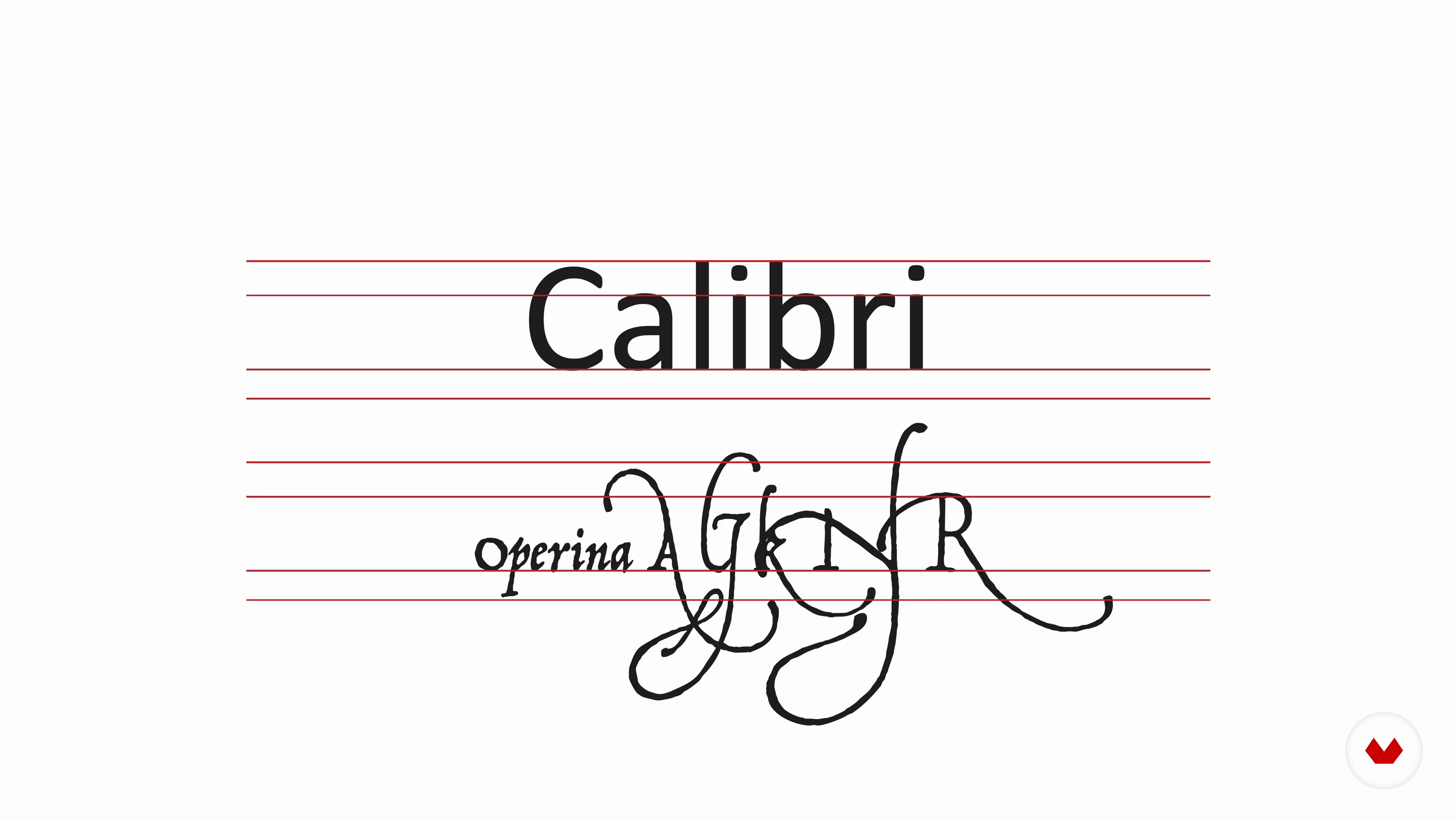
“Nu zal ik je helpen beslissen of je, in de huidige staat, een lettertype kunt maken met je handschrift, of dat het integendeel een aantal eerdere verbeteringen vereist.”
In deze videoles behandelt Cristóbal Henestrosa het onderwerp: Analyse van uw brief, dat deel uitmaakt van de online cursus van Domestika: Ontwerp typografie en digitaliseer je eigen letters. Zet je handgemaakte letters om in een unieke, digitale typografie die persoonlijkheid toevoegt aan alles wat je schrijft.
“Analyse van uw brief Aangezien dit hoogstwaarschijnlijk uw eerste benadering is om lettertypen te ontwerpen, wil ik je wat advies geven over hoe het leuk zou zijn als je zou beginnen met het overtrekken van je brieven. Het belangrijkste is dat de letters niet samenkomen zoals in het schrift dat we kennen als 'script' of manuscript. Het zijn erg mooie teksten, maar ze geven de moeilijkheid weer dat, aangezien typografie rechthoeken zijn die zijn samengevoegd, het is moeilijk voor ons om te bereiken dat ze allemaal harmonieus samenkomen. Zoals we al zeiden, de A kan een B of een C of een Z er...”